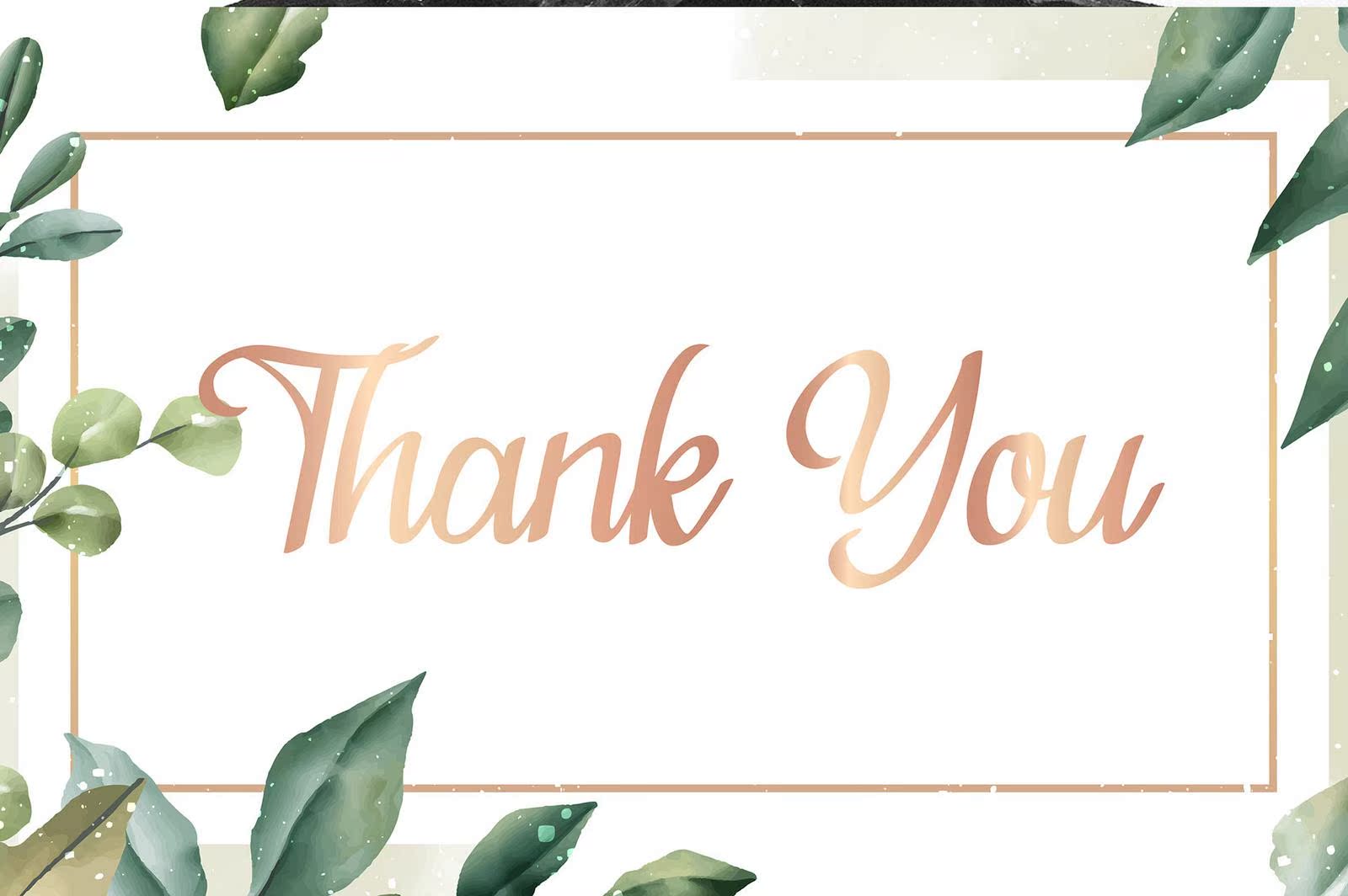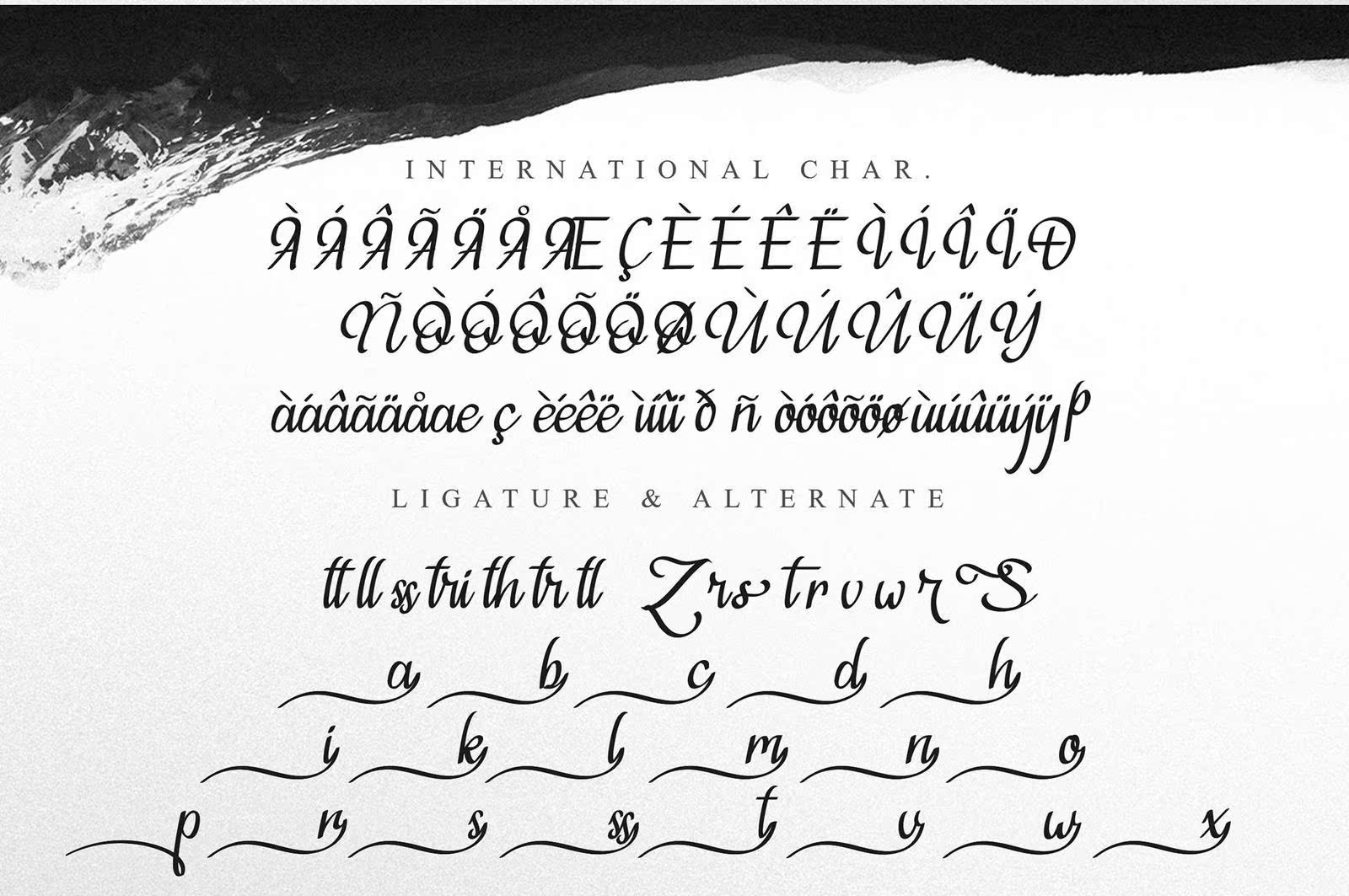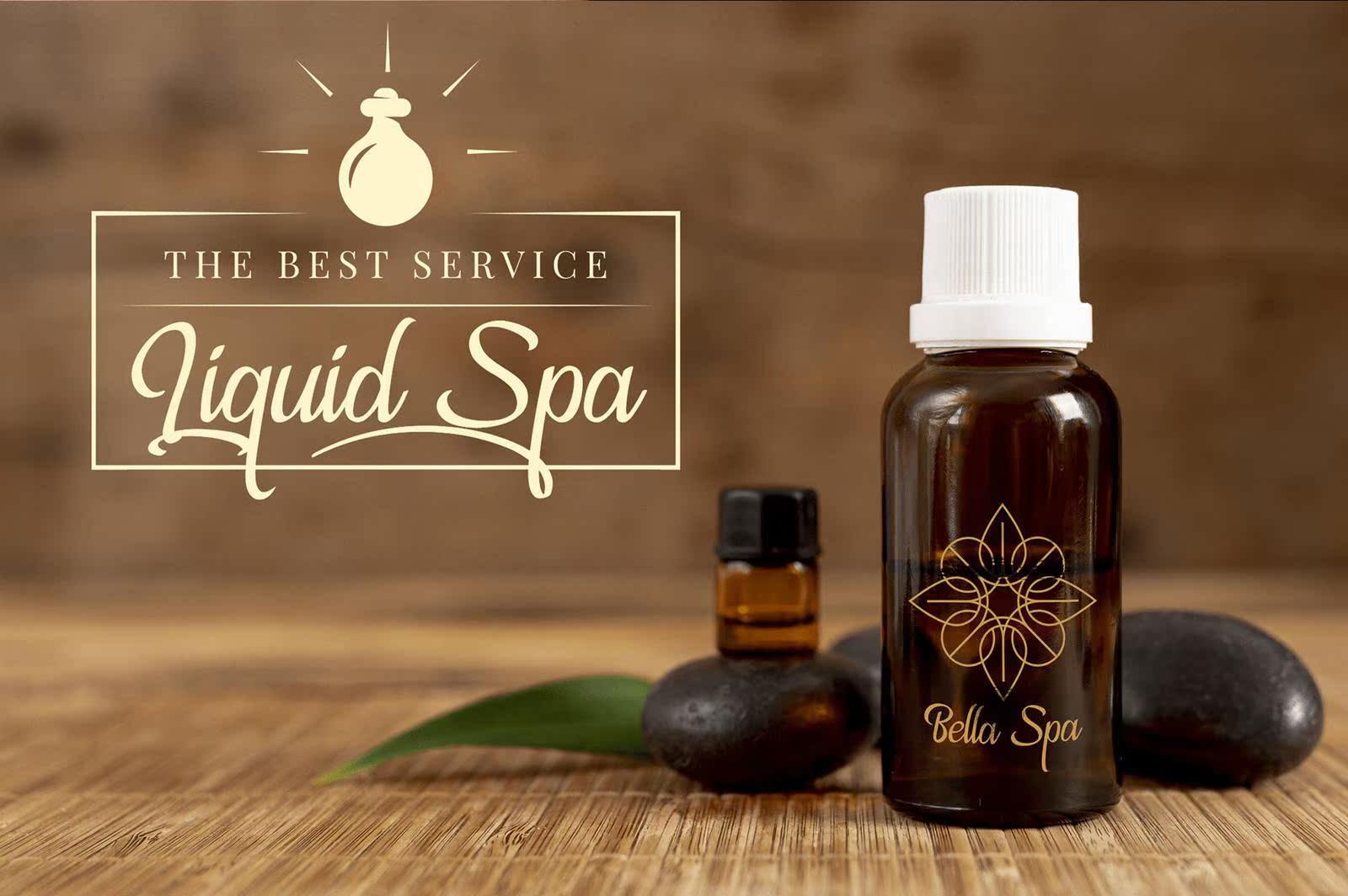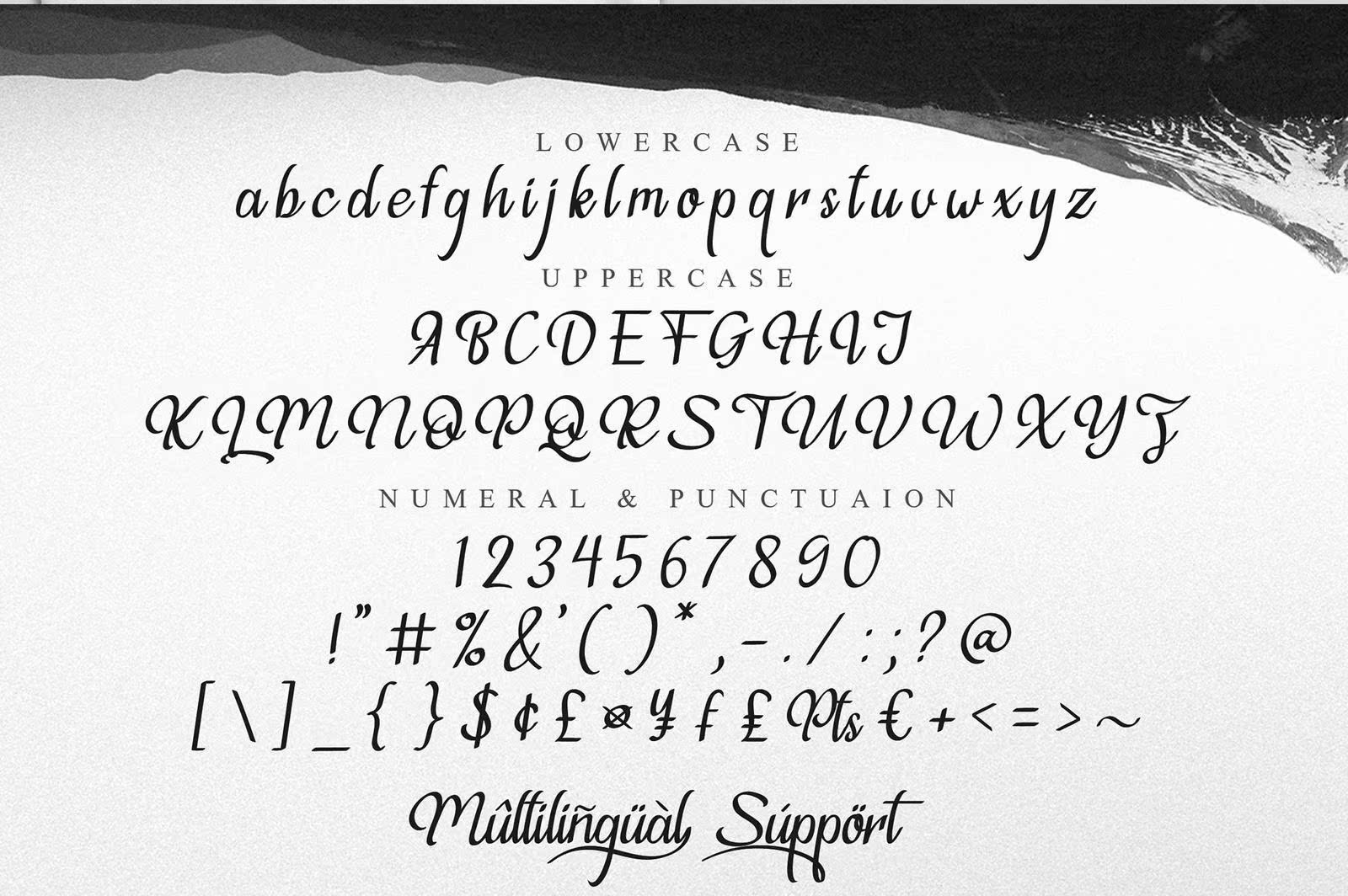
FreeViolleVascriptFontisaneLegant和ModernCaligraphyFont。它最适合品牌标识、t恤设计、海报、名片、排版、报纸和任何其他艺术项目!Voilleva会把任何创意都变成一件艺术品!。此免费字体在品牌项目、编辑设计、产品包装和任何其他项目需求方面都非常出色。与格式文件一起使用,也可以与WebFont一起使用。因此,此DemoFont具有个人使用许可证。但是,请不要错过购买PremiumVersion的更多功能。